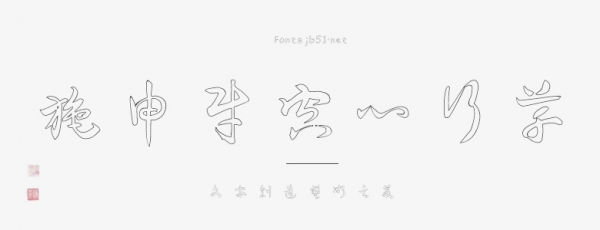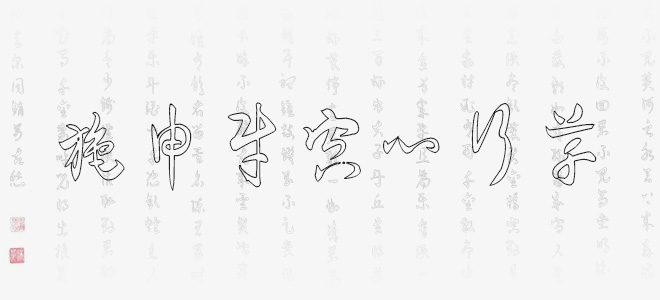
施申財(cái)空心行草是一款賞心悅目、百看不厭的空心行草體,字體線條粗細(xì)適中,筆畫(huà)隨性,結(jié)構(gòu)灑脫自在,具有很好的視覺(jué)感,適合于文化類(lèi)的宣傳設(shè)計(jì)、商業(yè)類(lèi)品牌的廣告和產(chǎn)品包裝設(shè)計(jì)以及個(gè)性化文字排版等較多場(chǎng)景。
施申財(cái)空心行草